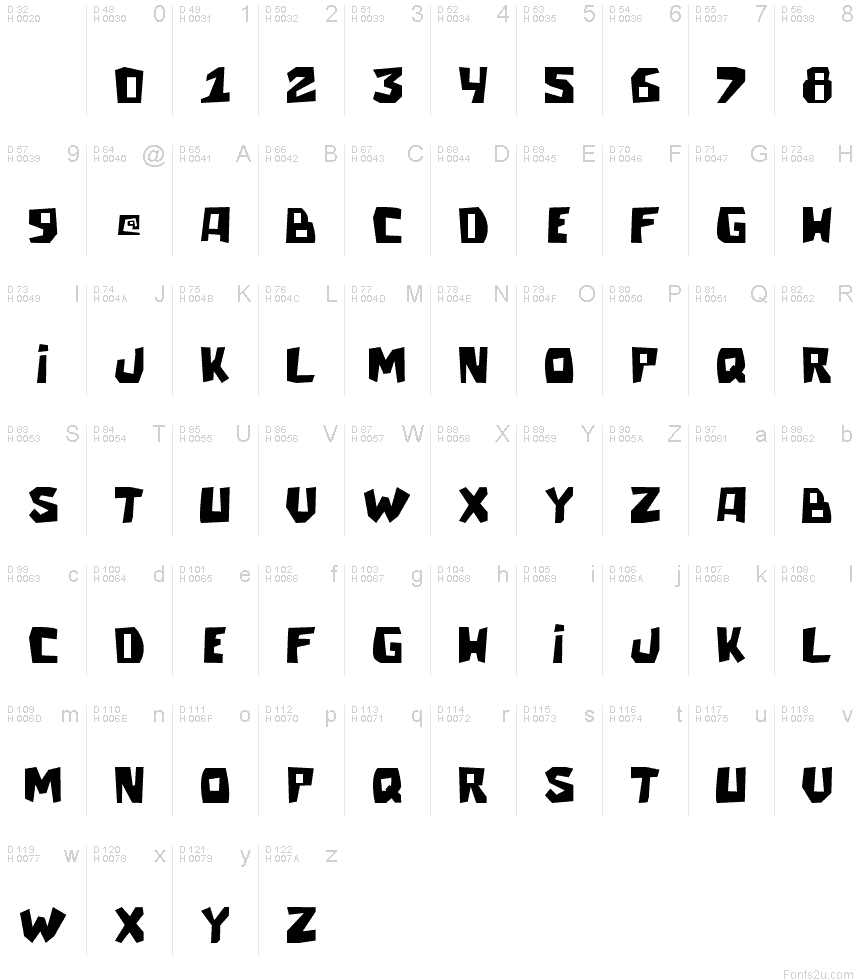
Talacha od Grafito Design je bezplatné display písmo s drsným vzhledem ručně vyřezávaných plakátů. Písmena jsou masivní a hranatá, se seříznutými rohy a nepravidelným rytmem, díky čemuž celý design působí svižně, hlasitě a správně „rozcuchaně“.
Hodí se pro grafiku, která potřebuje syrovou energii místo uhlazenosti: nadpisy letáků, skateboardové či hudební plakáty, obálky zinů, titulky a odvážné skici log. Jako bezplatný font funguje Talacha nejlépe v krátkých textových prvcích, kde mohou vyniknout tyto zubaté, improvizované tvary, zejména u titulků nebo monogramů, které chtějí působit jako ruční práce typu „vystřihni a nalep“.